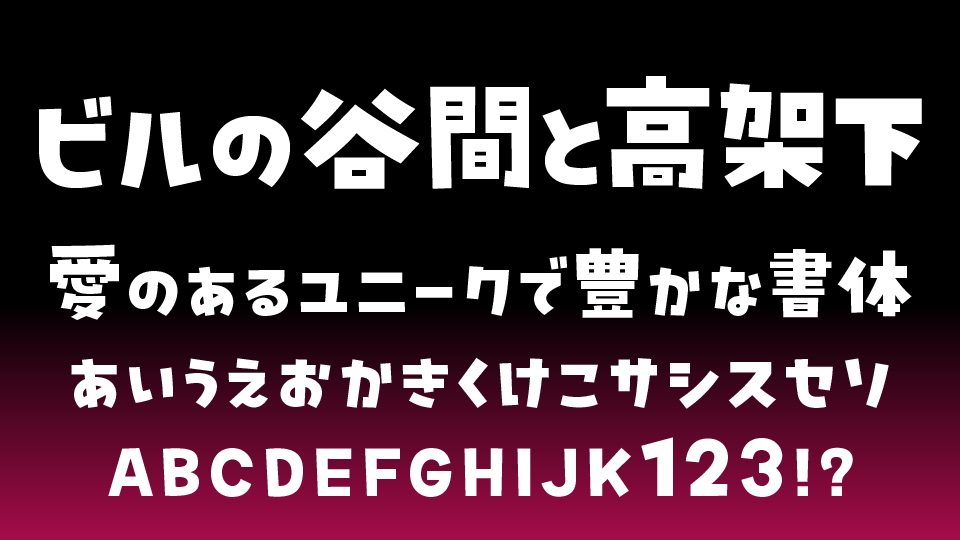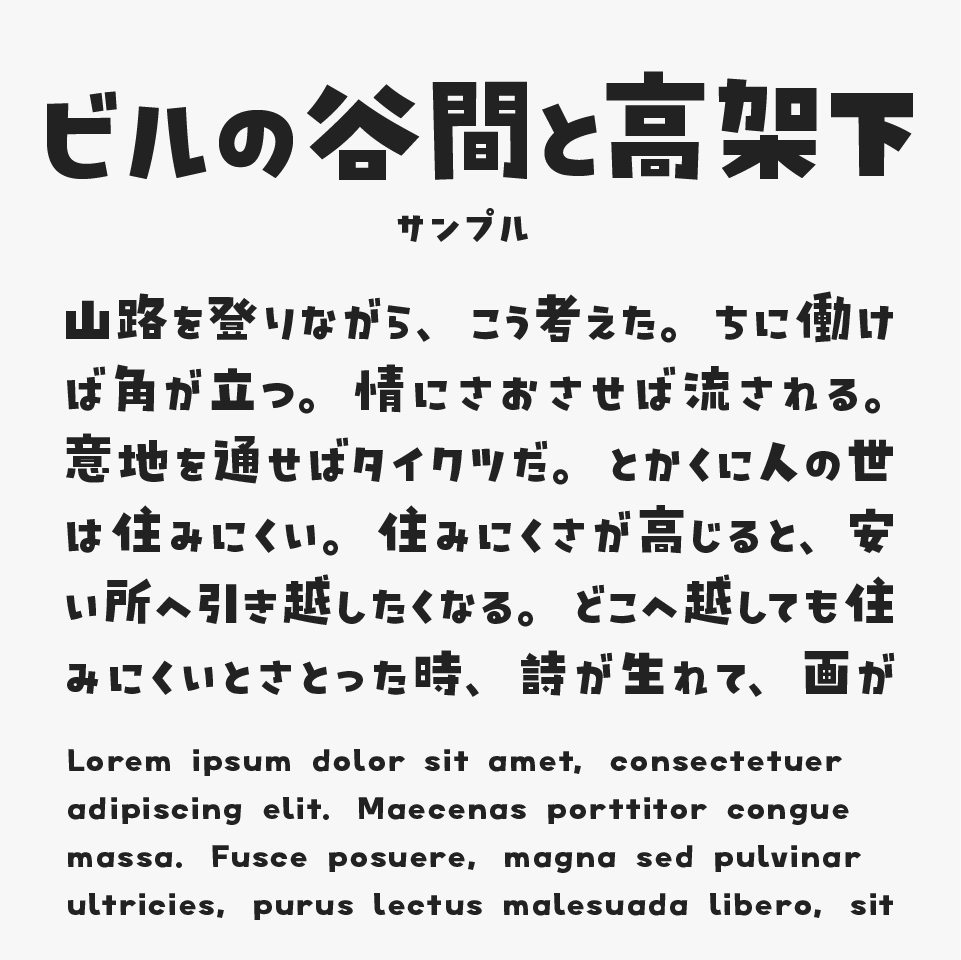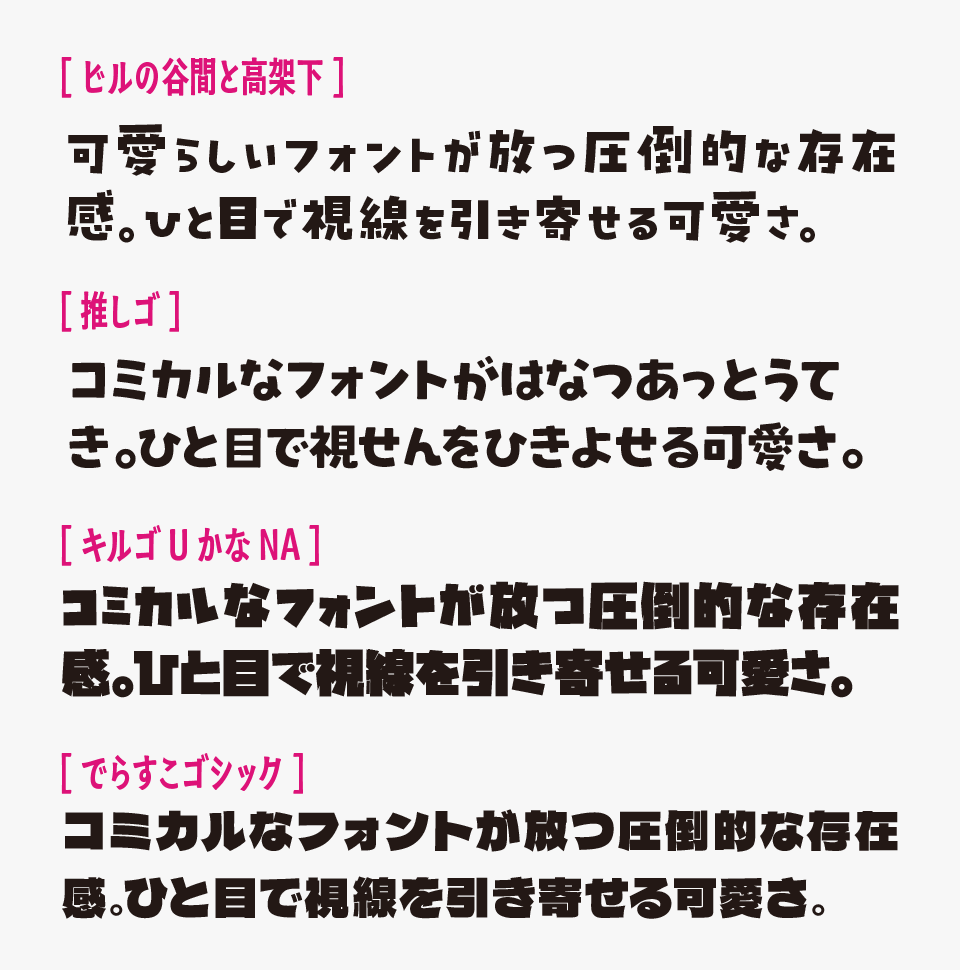
ビルの谷間と高架下フォントは、漢字・ひらがな・カタカナそれぞれのサイズ感やリズムに、あえて少しデコボコとした変化を加えた可愛らしいデザインフォントです。
直線的でスッキリした字形をベースにしながらも、文字ごとにほんのり個性を残したデザインになっているため、整いすぎない自由な空気感があります。きっちり並びすぎないことで、ポップで軽やかな印象が生まれており、見ているだけでも楽しくなるような雰囲気が魅力です。
あえて漢字とひらがな・カタカナのサイズ感を変え、でこぼこしている文字を組んだ際にリズミカルな様子が生まれて、文字から明るく楽しい様子が見えてきます。
インパクトがあるので、タイトルや見出しにも向いています。
動画のテロップなどにも使えそうです。かわいい!
ベタ打ちのままでも十分可愛らしいですが、文字に少し加工を加えるだけ、ちょっと印象が変わるので、色々試しても良いですね。
直線的で可愛らしいデザインフォントと比較してみると、「ビルの谷間と高架下」は、文字ごとのデコボコとしたリズム感が特に印象的です。(比較フォントは、推しゴ、キルゴU、でらすこゴシックと比較しています。)
収録文字は、ひらがな、カタカナ、漢字1000文字程度、英数字、記号が収録されています。